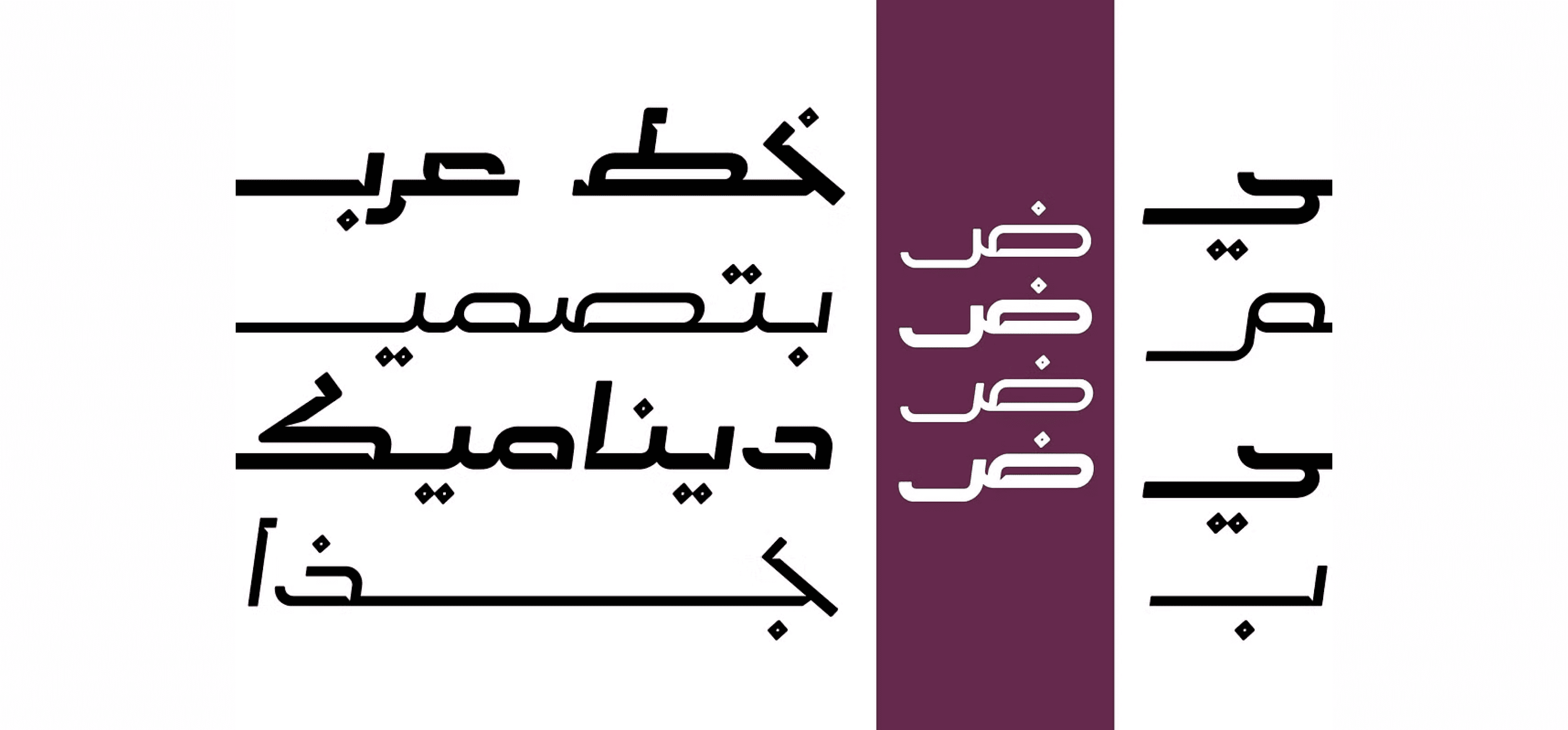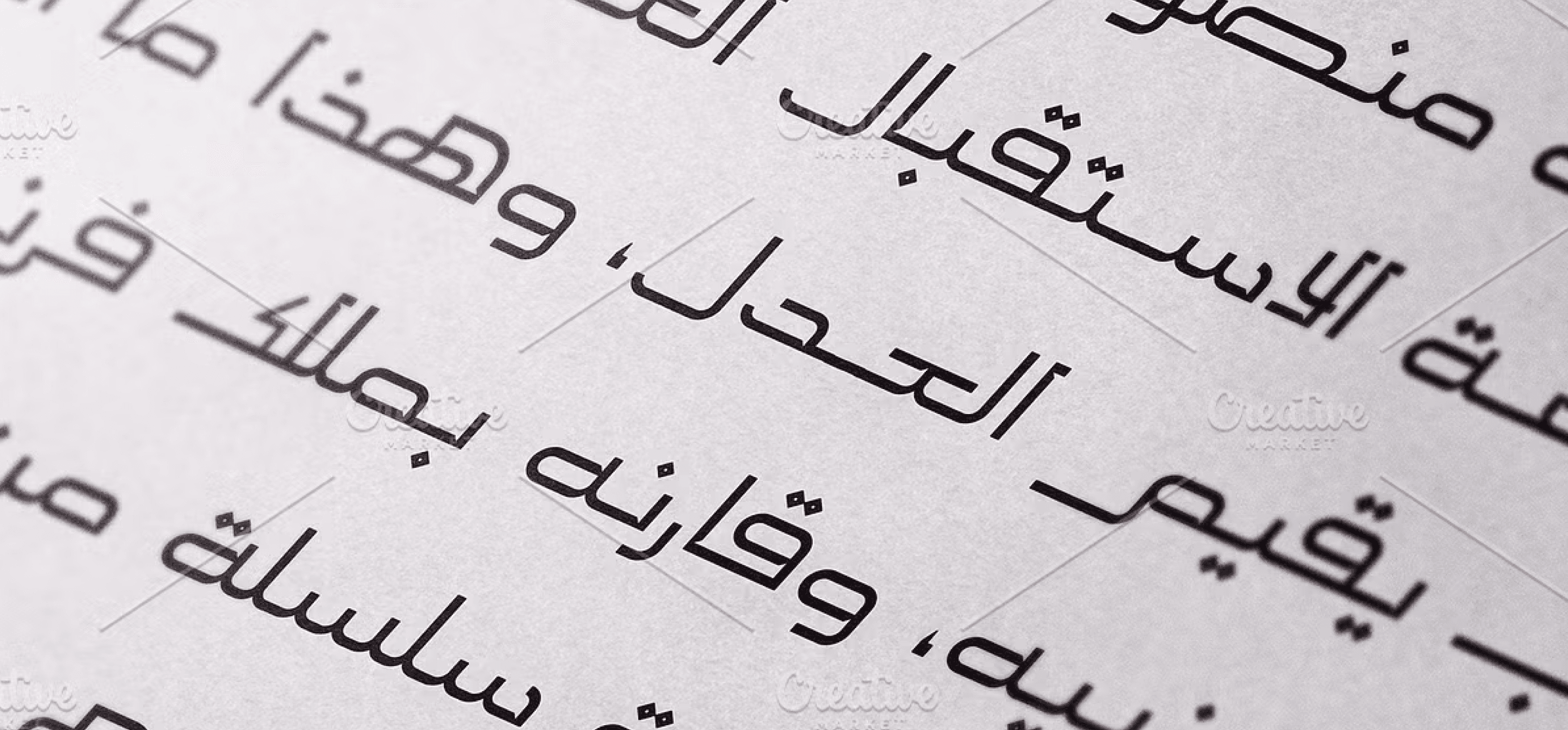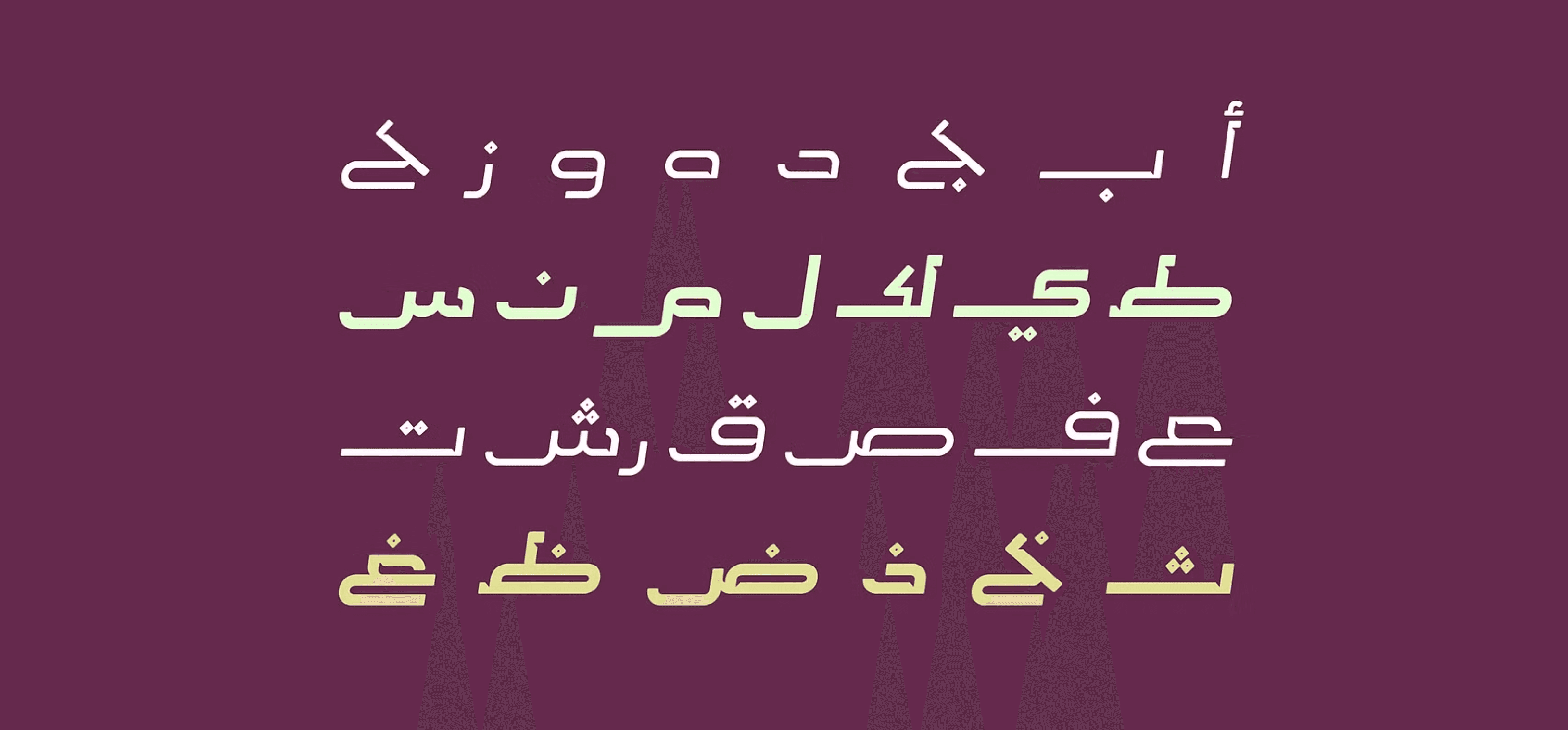
خط Malhooz هو خط عربي من فئة السان سيرف (Sans Serif) يتميز بتصميمه الهندسي الواضح والخطوط المستقيمة الدقيقة، مما يمنحه مظهرًا عصريًا ومقروئية عالية.
مواصفات الخط:
النوع: خط عرض عربي (Sans Serif).
الطابع: بسيط، هندسي، عصري.
الاستخدامات: مثالي للويب، الطباعة، التطبيقات، العلامات التجارية، والواجهات النصية الواضحة.
الأوزان: يظهر بمظهر موحد ومتماسك في كل وزنه.